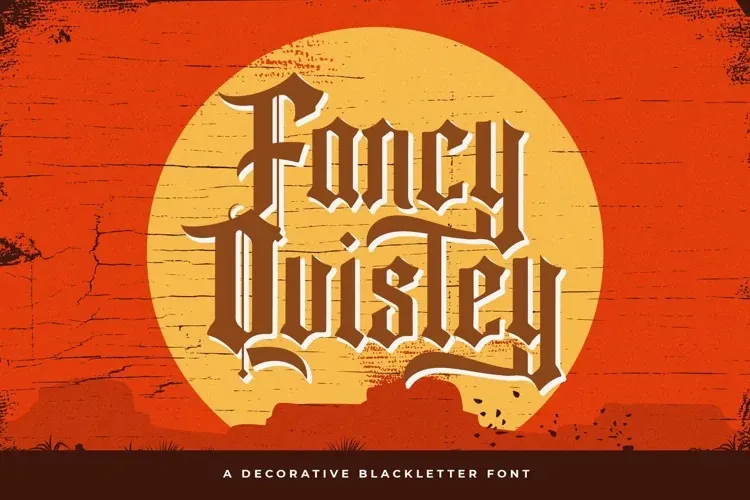
Fancy Quisley Font – Download Grátis
Esta é uma fonte chamada Fancy Quisley, criada por StringLabs e disponível no site 99designs. Seja para qualquer projeto que você esteja trabalhando, esta fonte moderna e distintiva pode revolucionar a maneira como suas ideias são expressas em texto. Com seu estilo chic e autêntico, é perfeito para dar um toque de luxo aos seus projetos digitais. Este blackletter (ou letra gothic) font apresenta um charme audacioso que certamente enriquecerá o visual de suas criações mais criativas e inovadoras. Add Fancy Quisley à sua biblioteca de fonts favoritas e veja como ela destaca seus trabalhos. Esta é uma ótima escolha para quem busca uma font moderna, vibrante e capaz de dar vida a qualquer ideia original que você possa ter. Com o seu uso, suas criações ficarão ainda mais sofisticadas e chamativas.